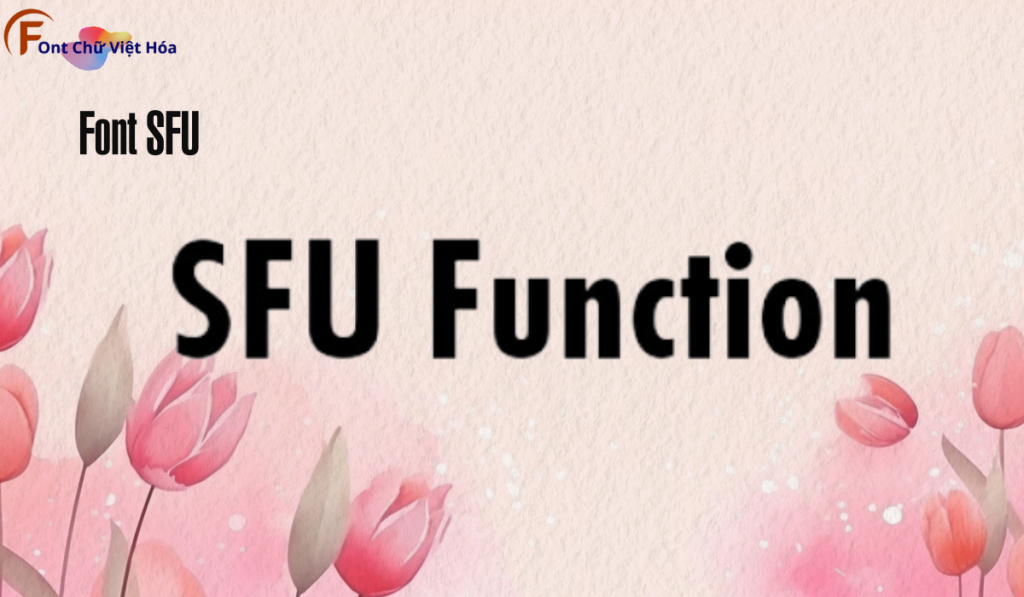
Bộ Font: SFU
SFU Function Việt Hóa, thuộc bộ font SFU, mang phong cách sans-serif hiện đại với các đường nét mạnh mẽ và cá tính. Font này được thiết kế nhằm mục tiêu tạo ra sự rõ ràng và dễ đọc, đặc biệt phù hợp cho các thiết kế như poster, logo, và tiêu đề. Đặc điểm hình dạng của SFU Function là các đường nét đậm và tỷ lệ chữ cân đối, giúp tối ưu hóa không gian và tạo ấn tượng thị giác mạnh mẽ. Font này cũng đã được Việt hóa, mang đến sự linh hoạt và tiện dụng cho các dự án thiết kế bằng tiếng Việt, giúp người dùng dễ dàng tiếp cận và sử dụng.